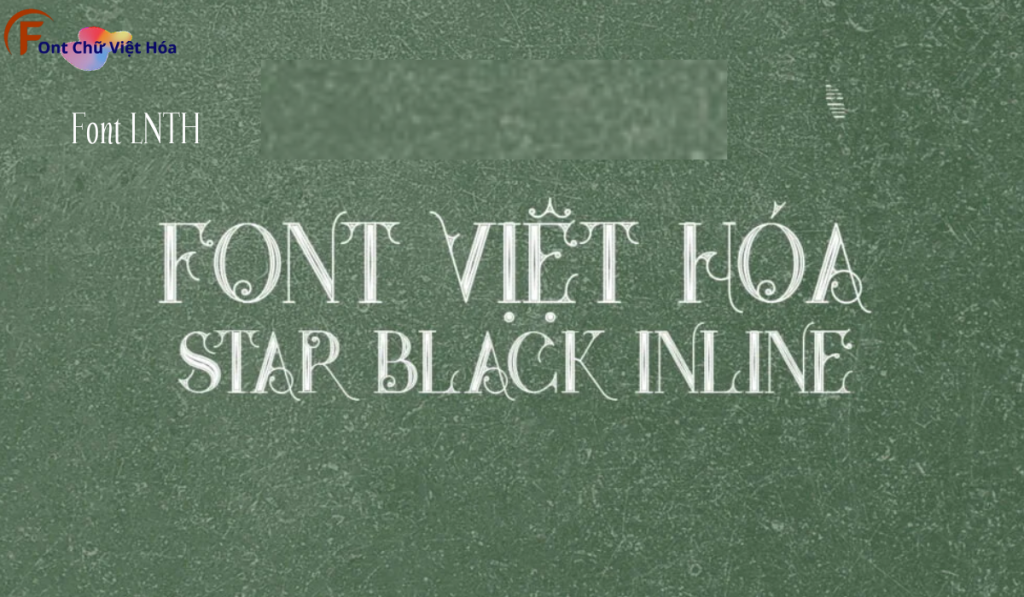
Font LNTH StarBlackInline Việt Hóa
Font LNTH StarBlackInline Việt Hóa là một font chữ độc đáo, thuộc bộ LNTH, với thiết kế đậm và ấn tượng. Phong cách của font này phù hợp với các dự án thiết kế cần sự táo bạo và thu hút, như poster, tiêu đề, hoặc bảng hiệu quảng cáo. Font LNTH StarBlackInline Việt Hóa mang đến sự nổi bật và dễ nhận diện, ứng dụng trong các lĩnh vực sáng tạo. Đặc điểm hình dạng của font bao gồm các đường viền nội bộ tạo nên hiệu ứng inline nổi bật, giúp tăng tính thẩm mỹ và sự chú ý. Việc Việt hóa font giúp người dùng dễ dàng sử dụng trong các thiết kế tiếng Việt, mang lại sự tiện lợi và linh hoạt.